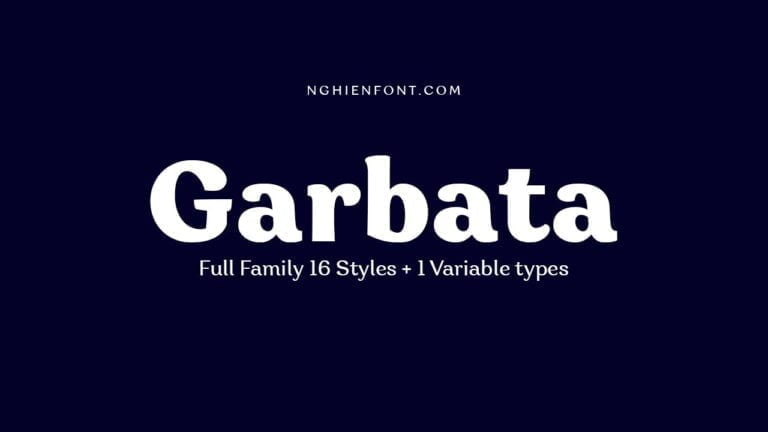
Garbata Font Family được thiết kế vào năm 2020 bởi Francesco Canovaro. Nó được dựa trên kiểu chữ cổ điển như Windsor hoặc Cooper, giữ nguyên hình dạng của một số chữ cái và thêm vào đó là nhạy bén của bút lông phẳng trong lĩnh vực chữ viết.
Kết quả là những ảnh hưởng lịch sử khác nhau này là một kiểu chữ sans serif độc đáo, được phát triển thêm một loạt các weight khác nhau, với sự khác biệt tinh tế giữa các phien bản medium, tập trung vào văn bản để hiển thị tốt hơn ở mọi kích thước khác nhau.
Được trang bị tất cả các tính năng OpenType tiên tiến mà bạn mong đợi, Garbata còn đi kèm với một bộ ký tự mở rộng bao gồm hơn 200 ngôn ngữ với các ký tự chữ latin và cyrillic.